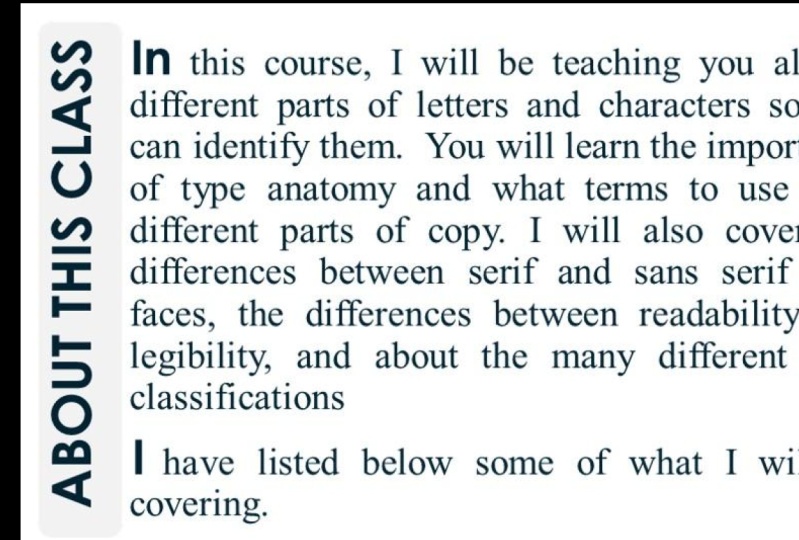
Anatomie et terminologie de la typographie
Introduction du cours
Classifications de caractères
Police de caractères, type Stlye, ou police
Anatomie des polices de caractères
Taille de caractères et mesures
Suivi de , Tracking, et direction
À propos de ce cours
Dans ce cours, je vous apprendrai toutes les différentes parties de lettres et personnages de lettres et de personnages afin que vous puissiez les identifier. Vous apprendrez l'importance de l'anatomie de caractères et les termes à utiliser avec différentes parties de copie. Je vais également aborder les différences entre les visages de caractères serif et sans seris, les différences de caractères entre la lisibilité et les nombreuses classifications de caractères différentes classifications de caractères
J'ai énuméré ci-dessous quelques-uns de ce que je vais aborder.
Terminologie
• Suivi
• Direction
• Le crénage
• Hyphenation
• Hauteur X-
• Base
• Vieux style
• Moderne
• Transition
• Stress
• Quad Em
• Grille de base
• Point vs Pica vs Inch
Anatomie
• Stem
• Bowl
• Crossbar
• Comptoir
• Ascender
• Descender
• Bras
• Oise
• Finial
• Course
• Boucle
• SERIF
• Spine
• Spur
• Caille
• Terminal
• Hauteur ascendant
• Hauteur X-
Type ouvert
• Ligature
• Alternatives contextuelles
• Ligatures de Discretionery
• Swash
• Alternatives stylistiques
• Tilter des alternatives
• Ordinals
• Fractions
1. Introduction du cours: Salut. Je m'appelle Josh Butts. Je suis graphiste et photographe. Et lorsque les aspects les plus importants de conçu pour créer une communication efficace peut être serré dans ce cours sera vous enseigner sur la typographie, anatomie et d'autres terminologie associés au type. Je vais vous apprendre comment le type est mesuré, les différentes parties des formulaires de lettres, quel suivi, laisser encourir moyens et beaucoup d'autres aspects du type de polices de caractères. Je vais également vous montrer quelques-uns de la grande ressource est que j'utilise pour trouver gratuitement des polices de haute qualité en ligne. J' espère que vous vous joindrez à moi pour apprendre tout ce que vous pouvez sur la typographie, anatomie et la terminologie. 2. Classifications de caractères: Bon, donc nous allons commencer ce cours en parlant des deux classifications les plus courantes de type, à savoir Sarah et Sansa. Et je vais le montrer plus tard pour que vous puissiez voir la différence entre ces deux classifications de type. Si vous remarquez sur les polices de caractères serif, vous verrez ces petites barbes ou serifis sur chacun des formulaires de lettre. Ces air appelé cirrus, et ils complètent habituellement les extrémités de chacune des formes de lettre. Et vous remarquerez sur San Sarah que les extrémités de chaque lettre sont simplement plates et qu'elles s' arrêtent complètement. Et l'une des façons les plus faciles de se souvenir c'est que Sands veut dire sans Sarah veut dire qu'elle a cette Sarah. Et souvent, quand vous parlez de polices de caractères San Serif, elles sont généralement appelées polices de caractères Sands. Maintenant, avec les polices de caractères serif et sans serif, il y a beaucoup d'autres classifications de types différents que nous allons examiner ici . Serif a beaucoup de styles différents en elle, et il y a, comme vous pouvez le voir ici, d' autres styles différents, et nous allons passer en revue ceux-ci un à la fois, donc vieux style est l'un des plus anciens types et vous pouvez voir qu'il est basé sur la façon dont ils construisaient le type quand ils ont commencé. Une des choses que vous remarquerez sur les polices de style ancien est la différence entre ces zones épaisses des formes de lettres et les zones les plus minces. n'y a pas beaucoup de contraste, et vous pouvez voir sur le Serifis juste ici. Ils sont assez organiques sur les formes. Juste courbe autour, et vous remarquerez également que sur certaines des formes de lettre telles que, Oh, est particulièrement, vous verrez un stress. Maintenant, nous allons parler du stress un peu plus tard dans le cours, mais comme vous pouvez le voir ici, cette ligne rouge montre le stress de ce Oh, qui fait référence à l'angle. Edwige. C' est parti. Vous pouvez voir ces zones épaisses sont sur le côté, et c'est là que les zones minces de la forme de lettre correspondent. Cela va vous dire où le stress de cette lettre forme. Maintenant. Un peu plus tard dans l'histoire, ils ont commencé à créer des visages de type transitoire et ce que vous pouvez remarquer à ce sujet est l' air de service. Beaucoup plus nette. Vous pouvez voir sur ce T leur service viennent au point direct, et il y a toutes ces lignes droites où ils courbent autour, et donc ils sont un peu plus pointus et direct sur le serifis que vous manquez aussi. Le stress sur ceux-ci est beaucoup plus vertical. En fait, c'est presque exactement droit de haut en bas, et donc vous pouvez le voir. Il devient un peu plus une police moderne avec les bords tranchants et la différence entre les zones épaisses des formes de lettres et les zones minces. Il y a beaucoup plus de contraste, et c'est donc l'une des façons de dire à quoi fait face un type de transition. Et dans ces exemples, j'ai pour l'ancien style. J' utilise l'ancien style Gowdy, et pour la police transitoire, j'utilise Baskerville. C' est une police transitoire très courante. Maintenant, nous passons ici dans les polices modernes, et vous pouvez voir qu'il devient un peu plus extrême avec le contraste et le serifis . Ces sérifis ici, comme vous pouvez le voir, sont très pointus. En fait, ils n'ont pas de transition entre le formulaire de lettre et la Sarah. Montez également ici, et vous verrez le stress sur les O est exactement droit et le contraste entre les domaines épais de la loi, réformes et les minces sont très contrastés. E. Et vous pouvez voir dans ces petites descriptions à quoi ressemble chaque classification de type et maintenant descendre ici un peu plus. Nous entrons dans les polices de caractères slab serif et vous verrez que le contraste sur les formulaires de lettre est un peu moins, mais vous en avez toujours une bonne quantité. Mais les sérifis sur ceux-ci sont très grands par rapport aux formes de lettre. Et c'est ce dont parle principalement Slab Serif, où il y a des formes géométriques épaisses, des sarah if et des lettres. Ce sont donc quelques-unes des polices de caractères serif les plus courantes que nous venons d'examiner. Maintenant, si nous venons ici, c'est une police San Serif, et celle-ci est Ariel, et c'est une police San Serif assez courante. Et ce que vous remarquerez sur les polices de caractères de San Serif, c'est généralement qu'il n'y a pas de stress pour les lettres du tout. Comme vous pouvez le voir beaucoup de ces formes de lettres, l'épaisseur est exactement la même partout, donc il n'y a pratiquement aucun contraste entre les zones épaisses et les zones d'aileron des formes Blatter . Maintenant, certaines des autres classifications différentes de type R script, et cela peut être écrit à la main ou des polices de caractères de calligraphie. Et ils peuvent avoir beaucoup de styles différents, qui reviendront un peu plus tard. Une polices de caractères décoratives. Une façon que vous pouvez dire si les polices de caractères décoratives, il aura généralement un seul style du fonds. Et donc, comme vous pouvez le voir, si je vais dans Ariel, nous irons dans les styles. Et il y a comme gras ou étroit italique mais décoratif. Si je vais dans les différents styles, il n'y a généralement qu'un seul style car ils ont été créés spécifiquement pour cela. Écoute, maintenant je reviens à la lettre noire, et c'est l'une des formes les plus anciennes de typographie, et comme vous pouvez le voir, c'est celle qui a été créée à l'origine. C' était une forme très artistique de type et nécessitait beaucoup d'habileté pour créer ça, et ça pourrait être vraiment bon pour des projets plus vintage ou quelque chose comme ça. C' était une forme très artistique de type et nécessitait beaucoup d'habileté pour créer ça, Donc Black Letter a beaucoup de courbes droites et un contraste très élevé entre certaines de ces zones épaisses et minces, et c'est un style très particulier maintenant. Le dernier type de classification de type examinera est les ornements, et cela peut généralement être construit dans deux autres polices de caractères. Par exemple, cet ensemble d'ornements est un grand ensemble dhoni d'ornements. Donc, cela vient avec que le fonds de donut, et généralement cela englobe juste un grand nombre de petits graphiques de sorte que vous pouvez utiliser avec différents types d'œuvres d'art et les résout ici. Et vous pouvez voir ces airs, les principales classifications de types que nous avons examinées. 3. Police de caractères, type Stlye, ou police: Et maintenant, nous allons regarder la différence entre une police de caractères et un plaisir. Et donc, comme vous pouvez le voir ici, sont des polices différentes que j'ai. Ainsi, une police de caractères va principalement se référer à la forme générale des formes de lettres. Donc, comme vous pouvez le voir, cette police de caractères est din et vous pouvez voir la lettre a comment elle s'étire un peu , puis se courbe autour. Alors que vous voyez Gotham, le est déjà courbé à partir de ce point, et le S a plus d'une courbe naturelle tout autour. Mais Dan a un type plus droit de courbes et de lettres droites forme des sables ouverts. Comme vous pouvez le dire, il y a cette petite coupe en haut de l'extrémité, et les esses sont un peu plus comprimées verticalement. Maintenant, on passe à cette autre police de caractères, Helvetica. Vous pouvez voir les lettres s'étirer autour de cette courbe sur le A, et il y a un peu plus de contraste entre les zones épaisses et minces de ce type. Ensuite, beaucoup de ces autres cas de type, et donc ces différentes polices de caractères ont des caractéristiques très distinctives. Maintenant, si nous allons dans certains des mêmes visages de type. Je vais conduire ça ici. Ce sont tous les mêmes visages de type, mais il y a différentes versions de celui-ci. Donc, comme vous pouvez le voir, cela a été alternatif et c'est un peu plus épais. Ce n'est pas pro, et donc ce sont tous les mêmes types de visage, mais leurs différents styles de celui-ci, et ils sont créés par des personnes différentes. Et donc, la façon dont des choses comme ça se produisent souvent est l'endroit où il y a des polices de caractères créées il y a longtemps , et les gens l'ont ramassé maintenant et en ont créé leurs propres versions. Et donc il reste toujours avec le même style où, comme vous pouvez le voir, huit s'étirent et se courbent ensuite, et c'est un dicton avec toutes ces autres versions de cette police de caractères. Mais beaucoup d'entre eux ont été créés par des personnes différentes, et il y a donc des différences subtiles, mais c'est toujours le même type de visage. Et maintenant, si nous parlons d'un fonds qui pourrait faire référence au style de type spécifique si nous parlons d'un fonds qui pourrait faire référence au style de type spécifiqueque nous utilisons sur ce sujet, donc si nous regardons ça,tout ça vient de la police centrale, que nous utilisons sur ce sujet, donc si nous regardons ça, tout ça vient de la police centrale, et chaque style fait référence à une police ou à un style de type Donc, si quelqu'un vous demande quel type de police vous utilisez sur un projet spécifique, vous pourriez dire que j'utilise central extra light métallique. Ou vous pouvez dire que vous utilisez Central Ultra. Maintenant, le groupe de tous ces styles de types dans un est appelé une police ou une famille de types, et cela fait référence à l'endroit où je suis Ah, en utilisant mon outil de type, et je crée un nouveau bloc de texte, puis je peux aller à Central. Et maintenant, j'ai tous ces styles différents dans cette famille de fonds central ou famille de type. Maintenant, une des choses que nous allons également regarder avec cela dans les styles de types est certaine. Les polices et les polices ont des styles de type différents. Et l'une des choses que vous voulez vous assurer est que vous utilisez les styles de types réels qui ont été créés avec le fonds. Et donc on va regarder ça, et c'est une police en italique, et vous pouvez voir que c'est vraiment une version, et celle-ci est fausse ou fausse. Et c'est donc ce mot photo ici est un terme commun pour le type qui se définit dans un style qui a été artificiellement créé de cette façon. Et maintenant, si on saute dans la boutique photo, c'est là que vous allez voir un peu de cette terminologie. L' utilisation est si je crée un type dans Photoshop et que je passe dans mon panneau de personnages, c'est marié. Pro et Aiken vont en italique juste ici, et ça crée son propre style de ça. Ou je peux remettre ça à la normale. Et puis je peux aller dans ce petit panneau latéral et cliquer ici faux italiques, et vous pouvez voir la différence entre ce que cela fait à ces deux polices de caractères est l' italique rial . Ses lettres ont construit une manière très spécifique. Donc ils ne sont pas étirés. Et ceci a été créé spécifiquement pour ce style. Ceci a dans la police de caractères standard a un style différent de a et il ne correspond pas aussi bien qu' en utilisant les italiques réelles pour cette police de caractères. Et si vous revenez dans Adobe Illustrator, nous avons beaucoup d'autres styles différents. Et ici, vous pouvez voir que c'est le pro adobe Gurman. Et ce qui s'est passé, c'est l'italique qui a été intégré avec le fonds, et avec cette italique, j'ai traversé et il est l'outil pur dans Adobe Illustrator et partagé cela un peu pour créer des italiques avec lui. Et il est donc toujours préférable d'aller avec l'italique qui a été intégré avec ce plaisir. Et cela va de la même façon avec les polices condensées et surtout avec quelque chose comme celui-ci, l'un des problèmes d'étirement car il peut vraiment déformer une police de caractères. Comme vous pouvez le voir, cette police de caractères que j'ai ici est Badani et est une affiche condensée. Et maintenant cette police de caractères sont ici est juste ne pas irrégulière et vous pouvez le voir avec cette police de caractères. Ces formes de lettre ont été construites spécifiquement autour de cette facilité d'air épais et mince de la police. C' est donc très proportionnel. Et avec cette version qui a été condensée ici, j'ai obtenu la police et je viens de l'insérer et elle étire la police et elle peut vraiment déformer les choses et causer des problèmes lorsque vous créez des illustrations. Et comme vous pouvez le voir, certains de ces autres problèmes que nous avons avec gras, il maintient toutes les formes de lettres cohérentes avec la police d'origine. Lorsque vous créez un fauxtexte en gras, les gens le font souvent en ajoutant un trait à ce formulaire de lettre, puis en augmentant simplement la taille de ce trait. L' un des problèmes que cela fait est qu'il commence à déformer la police en créant incohérences avec les zones épaisses et minces de plaisir. Et donc il devient presque un visage de type différent, et souvent il n'a pas l'air très bon de le faire de cette façon. Donc, surtout avec Bull, voulez-vous toujours utiliser la version originale de ce boulon ? Comme vous pouvez le voir ici, nous l'avons étendu, et c'est la même chose que je suis parti, et je suis juste allongé sur cette police, qui a étendu les tiges sur ces formes de lettre. Mais les lignes horizontales sur les formes de lettre ont été étirées encore plus minces. Maintenant, quand vous parlez de petites casquettes, comme vous pouvez le voir ici, ça devient un peu plus compliqué. Certaines polices n'ont pas de petites majuscules, et quelques fonds à faire maintenant. Cela pourrait être l'un des plus problématiques. Lorsque vous utilisez de faux ou ennemis petites capitalisations est comme vous pouvez le voir ici, cette police ici j'utilise riel petites majuscules, et les formes de lettre sont très similaires à l'épaisseur des lettres majuscules pleine taille ici dans ce faux petits casquettes composition, vous pouvez voir les petites capitalisations sont beaucoup plus petites et épaisseurs que les grandes. Et c'est parce que c'est juste le même type que les grands chats vient d'être réduit. Et cela peut créer l'amour. incohérences entre la composition et lorsque vous la lisez peuvent sembler assez mauvaises lorsque vous la comparez à la police plus grande, c' est pourquoi l'utilisation de petites majuscules riel est toujours la meilleure façon d'y parvenir. Maintenant, l' une des façons que vous pouvez dire si un plaisir a ou non de petites capsules intégrées est que vous pouvez monter à la fenêtre et vous assurer que vous avez, euh, sous le panneau de type. Vous pouvez aller à votre panneau glyphes. Et si je fais glisser ça ici, vous pouvez voir dans ce bailleur de fonds ici. Je vais cliquer dessus et je vais nous conduire un peu. Vous pouvez voir ici, nous avons ces petites majuscules juste ici dans le panneau des falaises, et cela signifie que cette police de caractères Ah , fond a riel, petites majuscules intégrées et d'autres polices comme celle-ci. Disons que j'irai à Gotham. Cela vous pouvez voir les petites majuscules ici sont beaucoup plus petites que le plafond pleine taille, et c'est parce que vous pouvez voir dans l'ensemble de paillettes il n'y a pas de petites majuscules intégrées dans le fonds, et ce qu'Adobe Illustrator fait automatiquement crée les petites majuscules. Lorsque vous êtes dans le panneau Personnages juste ici, vous définissez cela sur les petits camps. Il va automatiquement créer de petites bouchons à partir de n'importe quel plaisir que vous avez, c'est pourquoi il est important de passer à travers un panneau de verre et de vous assurer que vous savez que plaisir a vraiment de petites bouchons. Parce que si c'est le cas, Adobe Illustrator va utiliser ces vraies petites majuscules. Mais si ce n'est pas le cas, Adobe Illustrator va simplement mettre à l'échelle cette police de caractères l'une des choses les plus faciles à distinguer dans adobe dans le design. Si je vais ici, hum, je peux aller à mon panneau de préférences, et je vais aller au type avancé eso vous ouvrez vos préférences et cette section de type avancé , vous pouvez voir le petit ensemble de capuchons. J' ai mis cela à 100% et donc ce que cela signifie est quand il crée de fausses petites capitalisations, va mettre à l'échelle ces deux. Habituellement, il sera réglé à 70%. Hum, mais si je dis ça à 100% tout le temps, alors quand je clique ici et que je vais dans le panneau de mon personnage et que j'allume les petites majuscules, ça veut dire que ça va automatiquement mettre à l'échelle ces petites majuscules à ce que je mets à 100%. Et donc cette police de caractères, sbire pro il Ari a des petites majuscules intégrées, ce qui signifie qu'il va utiliser ces petites majuscules et qu'il a dit 100% de l'échelle qu'ils devraient être. Et cela signifie que ce sont des petites lettres majuscules pleine taille. Si je vais Teoh, dis Gotham, essayons juste Gotham Bold. Ces petites majuscules qu'il montre ici sont réglées à 100%, mais comme il n'a pas de petites majuscules , il est juste de mettre à l'échelle les lettres à 100%. Donc, vous n'aurez pas ce problème lorsque vous activez cette fonctionnalité. Et c'est aussi un autre moyen facile de savoir si oui ou non un correctif amusant ou de type a de petites majuscules intégrées en elle est par la mise à l'échelle de ces lettres. Et donc je vais essayer un autre. Baskerville vieux vite. Essayons juste. Je suis, oui, comme le texte Baskerville régulier. Et donc cette police de caractères n'a pas de petites majuscules intégrées. Bien, parce que ces air la pleine taille des majuscules. Et donc si je pouvais faire défiler certaines de ces différentes polices de caractères, la plupart de ces polices que je n'ai pas de petits camps par cet écran de cheveux fonder Playfair . Celui-ci le fait. Et donc ces air très légèrement plus petit que les bouchons de taille réelle. Mais vous pouvez voir que ce sont de vraies petites majuscules. Et alors revenons ici dans l'Illustrator et je vais zoomer. Je vous ai montré beaucoup de fonds différents que j'utilisais. Et maintenant je vais vous montrer quelques-uns des endroits où je trouve beaucoup de visages de très haute qualité. Souvent, on va y avoir tous ces styles. Donc, je vais aller à une nouvelle fenêtre de navigateur et l'un de mes sites préférés que je voudrais aller est polices dot google dot com. Et celui-ci a beaucoup de très bonnes polices de caractères dans beaucoup d'entre eux sont vraiment de haute qualité. Donc, dans ce site, l'un des déchets naviguer. Vous pouvez voir toutes les différentes polices ici dans l'écran principal, et vous pouvez le changer pour votre propre type. Donc exemple de texte ici et je peux appliquer cela à tous les fonds et avoir une très bonne idée de ce que je veux ressemblera à ce que je peux changer l'échelle de cela et appliquer cela à tous les fonds et voir vraiment à quoi ils vont tous ressembler. Et maintenant, si je veux filtrer ah, une certaine police de caractères que je veux. Je peux décocher ces différentes classifications de type et vraiment l'affiner. Une des choses que j'aime faire est de vérifier le nombre de styles parce que plus de styles de plaisir a, plus je vais avoir de flexibilité avec ce plaisir. Disons que je veux juste une police de caractères sands ou une police sans serif. Alors je peux vérifier ça, et je veux avoir beaucoup de styles. Et maintenant ce sont toutes de très bonnes polices de sable que je peux utiliser. J' aime son monstre dehors. Et donc si je clique dessus, ça va me montrer tous les styles qu'il a sur cette police de caractères. Et donc il en a beaucoup, en fait. Et c'est donc une ressource vraiment sympa où vous pouvez télécharger toutes ces polices gratuitement. L' une des autres ressources est que j'aime est l'écureuil amusant. Maintenant, écureuil de fonds a beaucoup de bons fonds. Beaucoup d'entre eux sont en fait des liens vers des fonds Google. Hum, et il a beaucoup d'autres très bons fonds gratuits sur Internet. Certains d'entre eux auront moins de styles, sorte que vous pouvez voir milkshake. Il s'agit d'une police décorative, et c'est une police de caractères de script parce qu'il n'y a qu'un seul style. Et donc si je clique dessus, vous pouvez avoir une idée de ce à quoi ça ressemble. Vous pouvez voir le nombre de styles et vous pouvez également filtrer les polices de caractères sur ce site Web à travers les différents styles similaires aux fonds Google. Donc, disons que je veux 12 styles ou plus et un plaisir Voici cet aileron amusant et je peux cliquer dessus et regarder quelques échantillons différents qu'il a, et je peux faire défiler vers le bas et regarder tous ces styles de type différents intégrés dans cette police famille, et ce que je peux aussi faire est de cliquer sur ce lecteur de test et d'essayer quelques-uns de mon propre exemple de texte juste là, et il va automatiquement le mettre à jour à tout ce que j'ai cet ensemble pour dire vouloir lourd et type 72 points, et cela va me donner un très bon échantillon, puis je peux télécharger le fichier de type ouvert. Et donc ce ne sont que deux vraiment bonne ressource est où vous pouvez trouver beaucoup de bons fonds de haute qualité pour vos projets. Cet air va généralement me donner beaucoup de styles et d'options différents pour travailler avec. Et si vous connaissez d'autres bons sites qui ont de bons fonds gratuits, hésitez pas à poster dans la section commentaires du cours afin que nous puissions jeter un oeil. Je vais donc revenir sur Adobe Illustrator dans la prochaine vidéo. Nous allons examiner certains des différents types de terminologie et d'anatomie des nouvelles formes de lettres 4. Anatomie des polices de caractères: Donc l'une des premières choses que nous allons regarder avec cette vidéo est comment le type est aligné. Et donc j'ai ce mot ici anatomie. Et si j'allume ces guides ici, vous pouvez voir les différents termes qu'on va passer. Hum, cette ligne de fond ici où toutes les lettres s'alignent s'appelle la ligne de base. Et je l'ai marqué juste ici. Et c'est la ligne que, comme vous pouvez le voir, la base de toutes ces lettres s'alignent jusqu'à cette ligne. Juste ici est la hauteur X, qui est l'endroit où toutes les lettres minuscules vont généralement correspondre à ou le X. C'est pourquoi on l'appelle la hauteur X. En raison de la norme X s'alignera de la ligne de base à la hauteur X. Cette zone ici est un ascender ou la hauteur du capuchon, où cette ligne sur le dessus est la hauteur officielle du capuchon. Oh, et très vite je vais te montrer un expéditeur D. Est une partie d'un formulaire de lettre qui s'étend au-dessous de la ligne de base et un US sous est une partie de ah forme de lettre minuscule qui s'étend au-dessus de la hauteur X, Cette ligne juste là. Et c'est donc ce que l'expéditeur est. Et voici les expéditeurs D. Et maintenant, nous allons revenir à notre couche d'anatomie sur cette zone où un centre comme cette lettre H que j'ajouterai juste ici. Vous pouvez voir cela correspond jusqu'à la hauteur du capuchon. Tout est sous cette véritable âme et rapide. Zoom ici et vous pouvez voir la hauteur de la cabine, la ligne de base, la hauteur X, l'Ascender ou le cap Hyatt juste ici où tout le haut correspond et la ligne de descente. Maintenant, avec des fonds différents, ils vont avoir des hauteurs X différentes et des ratios Ascender à la hauteur gardée. Donc vous pouvez voir et ces deux fonds ici, ils sont tous les deux de la même taille, les deux 87 points, hein ? Et vous pouvez regarder ça ici. Vous voyez que j'ai Baskerville et Helvetica. Et où la hauteur X correspond à Baskerville. Il est beaucoup plus bas là où la hauteur X est sur Helvetica et donc cela va faire une grande différence dans la façon dont vous allez vouloir définir votre type car le rapport de hauteur X sur Helvetica est beaucoup plus grand que sur le basket-ball. Et vous pouvez également voir que pour la même taille point Baskerville est un peu plus courte que la hauteur du bouchon sur Helvetica. Et donc ces différences aériennes, vous remarquerez dans les différentes polices de caractères. Et donc je vais les cacher et vous montrer cette prochaine série de lettres et vous montrer d'autres différences avec ces lignes. Donc ici, vous avez votre dissenteur et tous ces dissidents sur ces formulaires de lettre. Vous avez votre hauteur X sur tous ces éléments et votre hauteur de plafond, mais vous allez aussi avoir avec certaines polices et polices. Vous allez avoir différentes hauteurs de plafond et une hauteur centrale sur certains d'entre eux. Comme vous pouvez le voir ici, les majuscules sont toutes alignées sur cette ligne juste ici. C' est un combat de chat, mais vous pouvez voir ici où l'ascender il correspond pour aligner un peu plus haut que ça. Donc, si j'utilise mon outil de type et que je clique ici et un l qui va correspondre à ce même âge et vous pouvez voir comment le battage médiatique central peut souvent être la même que la hauteur du bouchon. Mais parfois, ce sera différent. Et c'est donc quelque chose que vous voudrez également surveiller lorsque vous créez un type dans vos projets. Et maintenant, nous allons y aller et regarder certains des différents termes anatomiques pour les formes de lettres minuscules. Et donc nous allons commencer ici avec le A et regarder les terminaux pour que vous puissiez voir la fin de la en fait ici, où vous pouvez voir la fin de l'E. Un terminal est la zone d'une forme de lettre où il se rétrécit et il s'arrête et va haut et montrez cette prochaine zone. C' est un taureau, et donc un taureau est en typographie, vu comme la partie incurvée de la lettre ou la partie circulaire qui englobe un compteur qui regardera dans une minute. Vous pouvez voir ici sur le P il y a un bol, et en fait, un taureau ferait également référence à cette courbe très sur le B. Vous pouvez voir sur le D. Il y a un taureau juste là et sur le remède. Il y a aussi un bol, et nous allons zoomer sur le A et haut que et vous montrer l'éperon. Ainsi, en typographie, un éperon est un petit élément de type projection qui se détache du trait principal. Et la prochaine chose que nous allons regarder, c'est la barre transversale. Maintenant à travers la barre est un trait horizontal sur une forme de lettre comme celle-ci, où il entoure une zone. Et sur cette lettre, vous voyez aussi qu'il y a cette petite zone englobée qui est appelée sur I. Maintenant, quand je parle aussi d'un compteur mais spécifique à la chaleur de la lettre, ce qui nous amène en fait à regarder un compteur. C' est ici connu comme un compteur ouvert, et ainsi de suite. compteur ouvert comme celui-ci est l'espace partiellement ouvert qui est à l'intérieur d'un personnage. Mais c'est ouvert à un bout, et nous allons regarder ça juste ici. Vous pouvez voir que cette zone qui est ouverte est appelée l'ouverture, et l'Apatow fait référence à l'écart qui crée un compteur ouvert. Maintenant, nous allons les cacher et vous montrer. La prochaine chose avec les compteurs est les compteurs fermés maintenant. La plupart de ces formulaires ont des comptoirs fermés. Vous pouvez voir dans le O et le G, Aussi dans le p Q B amedy ces air tous les compteurs proches, qui est une zone qui est juste complètement enfermé par un personnage. Je viendrai au F comme on l'a dit tout à l'heure. Ceci est connu sous le nom de Sarah et sur le F. Il y a aussi un trait transversal, euh, maintenant à travers le trait est une ligne horizontale dans une forme de lettre similaire à la barre transversale, mais il n'est pas inclus dans la forme de lettre. Donc, comme vous pouvez le voir dans la lettre T, il y a aussi à travers le trait juste là maintenant, aussi particulier à la lettre F. Vous verrez que cette partie supérieure est connue sous le nom de fenouil. Fenouil est la partie supérieure de la courbe de assez qui arrive à une fin et passant à la lettre G. Il y a quelques parties différentes de la lettre G que vous verrez sur le dessus est le taureau, mais sur le fond est appelé une boucle, et maintenant boucle est un particulier à un G minuscule dans la plupart des polices de caractères, où il y a ce qu'on appelle une forme de lettre à deux étages. Maintenant, la forme de lettre de deux histoires est là où il a deux de ces parties. Comme vous pouvez le voir dans cette lettre ? R. C'est ce qu'on appelle deux histoires A Non. Si j'ajoute un autre type de dans un, euh, je vais le conduire ici, et je vais l'agrandir et ensuite je pars. Teoh, utilisez un Berlin Sands. Maintenant, c'est ce que vous appelleriez juste une seule histoire où c'est seulement dans la partie inférieure de la forme de lettre, où c'est une histoire de deux. Ça reviendra ici à la prison où c'est une lettre de deux histoires. G sur la boucle sur un G est la zone complètement fermée qui est généralement inférieure à la ligne de base, ce qui serait là où le bas de ces lettres se réunit. Et maintenant sur une double histoire G, où cela se connecte ici, la boucle et le taureau est appelé un lien et voir l'énergie concessionnelle. Il y a en fait beaucoup de termes différents quand on fait référence aux différentes parties de celui-ci , surtout cette petite zone juste ici en haut du G est connue sous le nom d'oreille. Maintenant, les années que l'on trouve habituellement sur la lettre J, et c'est un peu décoratif sur le dessus du bateau, donc je vais les cacher maintenant et nous allons passer à la lettre G. Et vous pouvez voir que c'est similaire dans certaines de ces autres lettres s'appellent L'Épaule. Maintenant, l'épaule est un coup de courbe qui commence à la jambe d'un personnage comme lettre N ou H, et même dans la lettre M et un coup de foot qui vise vers le bas sur ces lettres et je vais zoomer sur la lettre I et toi peut voir cela le petit point sur le haut de la minuscule Ira J, est appelé un point ou un tittle, et c'est donc assez explicatif. Maintenant, dans cette lettre suivante, voici Ah, lettre J minuscule La petite extrémité effilée d'une forme de lettre s'appelle la queue Vous pouvez voir sur la lettre minuscule T . Il y a aussi une queue. Et si vous descendez à la lettre, pourquoi vous pouvez voir un conte qui descend en dessous de la ligne de base  ? Cela reviendra ici et ira à la lettre suivante sur une lettre K. Vous pouvez voir une tige est une barre verticale primaire sur une forme de lettre. Donc, comme vous pouvez voir la tige de la lettre, je suis juste ici. Et beaucoup de ces autres formes de lettre ont une tige. Aussi, vous pouvez voir ici sur la lettre f sur l'être ces air toutes les tiges primaires de ces lettres. Si vous revenez, nous allons voir maintenant la jambe est la partie en pente vers le bas de forme de lettre ah, généralement sur Ah que ou les majuscules sont qui ralentit de la lettre. On va passer à la course. Maintenant. Le trait est sous toutes les formes de lettre. Généralement, un trait est une partie principale du formulaire de lettre qui crée la lettre dit que vous pouvez voir dans le P. Le trait est ce qui constitue cette lettre. Et dans le O maintenant, pendant que nous regardons le oh, nous allons regarder le stress comme nous avons parlé plus tôt. La contrainte est une diagonale, une inclinaison de n'importe quelle forme de lettre. Donc, si vous y pensez, j'ai téléphoné. Il aurait beaucoup plus de stress que ces formes de lettre maintenant pour venir ici à la s. Ce trait ici est le trait principal de la courbe de la minuscule, ou lettre majuscule s qui est connu comme la colonne vertébrale et vous verrez. Aussi dans la lettre s est un bec. Maintenant, le gros est l'éperon pointu qui se trouve habituellement en haut des lettres dans ces formes de lettres romaines . Maintenant, nous allons venir ici aux dernières lettres de l'alphabet où nous allons voir sur le V et le W aura. Vertex est le Vertex est généralement juste le point extérieur au bas d'un personnage où deux de ces traits se rencontrent. Et de l'autre côté, vous verrez l'entrejambe juste ici, aux Émirats arabes unis. L' entrejambe est cette zone de la forme de lettre sur le dessus de l'endroit où deux de ces coups de viande et créer cette partie du comptoir. Et la dernière chose L. C dans ces lettres est le trait diagonale. Et c'est la même chose que vous verrez dans ces autres coups juste ici. Le trait diagonale est sur ces lettres en bas, où le trait primaire principal est en diagonale. Et donc, zoomez sur toutes ces formes de lettre et nous les cacherons. Et maintenant, regardez les formes de lettres majuscules. Et donc nous allons recommencer avec un vous remarquerez avec une majuscule. R. C'est comme un V à l'envers où ? En bas de la vue. Tu te souviens qu'on avait eu le Vertex juste ici ? Eh bien, avec un A, le sommet de ça va être appelé les animaux de compagnie A. Et c'est ce que vous appelez la zone du sommet. Où diagnostiquer les coups d'une lettre pour la viande. Et encore une fois, comme nous l'avons vu, nous avons la barre transversale sur un qui est le trait horizontal qui traverse une forme de lettre. Et on va bonjour, Viz puis on a la lettre C. On a notre comptoir ouvert et la zone où il ne se connecte pas s'appelle l'Apertura. Et vous avez nos comptoirs de vêtements, euh, dans la lettre o et dans la lettre Q, où l'intérieur de la forme inférieure est complètement fermé. On va les prendre maintenant et regarder le bol. Donc, beaucoup de ces termes que vous pouvez voir sont assez similaires à partir des lettres minuscules. C' est sur la minuscule A. Il y a un éperon et vous pouvez voir dans un certain nombre de cas Gee, il a aussi un éperon qui s'étend à partir de cette forme de lettre. Il y a des queues sur la lettre J et la lettre Q comme une queue très particulière dessus, qui est assez perceptible. Et sur la lettre K, comme nous avons parlé il ya ah, jambe, jambe, et en majuscules, les lettres sont vous pouvez aussi voir que la jambe maintenant les tiges sont les mêmes barres verticales droites sur les formes de lettre Comme vous pouvez le voir ici dans la lettre T et dans la lettre l un des différents termes que nous allons regarder ici, cependant, sur la lettre l est cette zone juste ici qui s'appelle le bec. Et comme il a vu que sur la lettre s dans l'ensemble précédent de lettres minuscules juste ici à la fin de ce s est un bec. Eh bien, une lettre majuscule. J' ai aussi ce gros maintenant. Eh bien, nous sommes de retour ici en regardant Serifis. Je vais vous montrer ces zones sont appelées parenthèses et c'est une distinction d'un serif où un surf pourrait être exactement droit ou les crochets pourraient être inclinés un peu plus dans la lettre o, nous avons du stress, qui est l'angle de celui-ci et qui passe à la lettre s. Il y a la même colonne vertébrale, qui est ce trait incurvé primaire qui compose la lettre dans la lettre T. Nous avons un bras maintenant le bras est vers le haut. Course inclinée ou juste droite vers le haut qui ne se connecte à aucun autre trait de part et autre. Donc, sur cette lettre, vous pouvez voir qu'il a un bras ici, et de l'autre côté de ce serait un autre bras les connaît. Et nous avons regardé cela avant le sommet sur le V et sur le bas de la W. Il y a aussi ces deux Vertex est, Et sur la lettre Z, nous avons la même diagonale frappé que nous avons vu dans la forme de lettre minuscule. On va cacher ça. Et maintenant, regardez ces deux types quelque peu uniques de ces formulaires de lettres avec nous. voyez, vous pouvez voir cette zone qui s'appelle la barbe qui est un serif qui vient autour et qui pointe vers le haut sur la lettre C et vous pouvez voir à quoi ça ressemble. Un peu comme une barbe. Et pour certaines lettres ou fonso, vous aurez la zone Vissel qui s'étend de différentes formes de lettres qu'on appelle un swash, et il se trouve généralement dans des visages plus décoratifs. Ou parfois il y aura différentes options pour certaines polices de caractères que vous pouvez y ajouter une neige fondante . C' est également le plus courant dans les polices de caractères de script qui vont avoir ces lavages de différence. Donc, je vais faire un zoom arrière, et maintenant nous allons regarder quelques différentes fonctionnalités de type ouvert. Ainsi, lorsque vous installez un fonds, la plupart des polices seront soit de type vrai, soit de type ouvert. Si vous avez un front de type ouvert, vous pouvez aller sous la fenêtre et aller à votre panneau de type ouvert, eso, qui tout tirant juste ici. Et je vais vous montrer comment utiliser quelques-unes de ces différentes fonctionnalités avec vos polices de caractères . Donc la première chose que nous allons regarder, c'est ici, et ce sont des ligatures. Ainsi, les ligatures ont été créées par des concepteurs de type lorsque deux lettres qui étaient à côté de l'autre causent des problèmes quand elles se rapprochaient vraiment. Vous pouvez voir ce que j'ai sans effort ici quand ils sont à côté de l'autre qui est si proche qu'il crée cet espace inconfortable. Et donc ce que les concepteurs de type ont fait est créé dans beaucoup de fonds différents. Ces ligatures, qui sont des connexions entre les lettres qui peuvent causer des problèmes quand elles sont trop proches les unes des autres. plus souvent ces lettres R fl si j'impliquais habituellement la lettre f et L, et quand vous tapez où vous pouvez faire est, ah, je vais aller à mon outil de type, Et je vais juste commencer avec beaucoup dans pro parce que c'est une très bonne police pour montrer cet exemple avec, et puis je vais juste cliquer ici et taper F f l. Et vous pouvez voir ici. Il n'utilise pas les ligatures parce que j'ai dans mon panneau de type ouvert, les ligatures juste ici, liqueurs standard sont désactivées, et de cette façon ces lettres ne font que taper les lettres standard de la police. Donc Aiken Dio est supprimer ceux et allumer les ligatures. Et puis quand je tape appel comme ça, ça va automatiquement les connecter quand je n'ai qu'une seule lettre. Il tape simplement la lettre standard, mais il peut automatiquement reconnaître quand une ligature est nécessaire, en fonction des lettres qui sont à côté de l'autre. Donc si j'avais un L ça va automatiquement connecter ça ou un F et un oeil. Il relie automatiquement ces lettres. Donc je vais juste dilater ça et revenir. Et donc ce sont des ligatures. La prochaine chose que vous pouvez regarder est juste ici est des alternatives contextuelles. Et je vais te montrer dans ce fonds juste ici. C' est Aphrodite E. Et si je les supprime et que je tape simplement un s standard, c'est juste un s standard de la police. Mais si je tourne sur des alternatives contextuelles, alors va ajouter une des formes de s alternatives pour ce visage de type. Et si vous allez dans votre panneau glyphes sur votre type de fenêtre et vos falaises, alors je peux le faire glisser. Vous pouvez voir ici pour que si je sélectionne cela, vous pouvez voir qu'il est juste ici dans la police de caractères. Et si je vais sous ce petit panneau juste ici où il dit montrer et ce menu déroulant, je peux trouver toutes ces alternatives goto alternatives, ou je vais en fait aller alternatives pour la sélection actuelle. Et je vais zoomer un peu et vous pouvez voir Ce sont quelques-unes des différentes alternatives que vous pouvez utiliser. Et si vous utilisez la dernière version d'Adobe Illustrator simplement en sélectionnant une lettre, vous pouvez consulter automatiquement certaines de ces différentes alternatives ici. Et c'est la bonne chose à propos du panneau de type ouvert est Vous pouvez vérifier cela sur. Donc, par défaut, va utiliser les alternatives intégrées pour cela, et vous pouvez passer par et je change manuellement celles que vous voulez. Et donc toutes les polices ne vont pas avoir toutes ces options différentes. Vous pouvez voir que j'utilise le lierre d'effort, et il n'a pas le Zordon ALS ou les fractions. Et donc, selon le type de visage que vous avez, cela déterminera quel type d'alternatives vous avez pour cela. Donc, je vais déplacer cela ici, et c'est un similaire avec une alternative stylistique utilise à ST Method cette police de caractères adobe un pro du gouvernement. Et donc si je l'aime juste là et éteins les alternatives stylistiques, alors ça va juste taper un e régulier. Mais si je l'allume, alors va ajouter une petite alternative vous à cette forme de lettre. Ou je pourrais ajouter un R ou l'activer et à un autre type de dans notre et ainsi avec une alternative contextuelle et stylistique, comme vous pouvez voir que vous pouvez facilement accéder à quelques options différentes pour certains fonds assez facilement juste en vérifiant ceux sur assez. Et ce sera la même chose avec ces autres types de lettres utilisant ligatures discrétionnaires. Ceci est similaire à la F et je est ensemble avec la mer et ce thé. Si j'ai vérifié ça ici, ligatures discrétionnaires et je m'en fais sans, alors ça va relier ces lettres ensemble. Vendu. Supprimez-les ici. Maintenant, plus tôt, nous avons parlé de swash is et des formes de lettre, et c'est de retour avec la police Aphrodite E à nouveau, et c'est juste une forme de lettre régulière. Mais si je vérifie le swash est des alternatives juste ici. Swash. Ensuite, quand je tape une journée, cela va ajouter une croix différente sur ce formulaire de lettre, et cela peut vraiment vous donner beaucoup de flexibilité lors de la création de certains paramètres de type pour créer un type amusant et artistique. Maintenant, on va aller voir les fractions et les polices de caractères Gordon ALS auront deux types de lettres et une barre oblique entre elles. C' est fait spécifiquement pour les fractions. Donc beaucoup de gens vont parfois taper une fraction, et ils vont simplement aller ici et taper, vous savez, cinq barre oblique huit. Et ce n'est pas la bonne façon de faire une fraction, parce que ces caractères standard de l'air et ils ne seront pas une fraction complète de la façon dont il devrait être tapé. Et ce n'est pas la bonne façon de créer des fractions. Une des façons de le faire de la bonne façon est d'entrer dans une police de caractères. On va cliquer ici, et tu trouveras le poste. Et il y a toujours un numérateur et un dénominateur lors de la création de fractions. Donc, si je vérifie le numérateur et que les nombres que je tape seront dans la position de numérateur d'une fraction. Et donc je suis et laisser ces et de créer le SLASH. Si vous ne voulez pas aller dans le panneau des falaises et essayer de trouver ces différents personnages, Aiken sur un Mac et un PC, je peux juste appuyer sur option ou arrêter et déplacer et un et cela va créer la barre oblique juste ici, qui est une barre oblique qui ira entre une fraction. Et je Si je vérifie ma position sur le panneau de type ouvert et avait dénominateur et je tape un autre nombre, il va être dans la fraction exacte Foreman et la façon dont vous pouvez vérifier que ces fractions ont été créées juste est que vous pouvez aller dans le panneau glyphes et tous zoomer un peu et aller à l'endroit où se trouvent certaines des fractions pré-construites. Et je vais juste taper trois forces et vous pouvez voir qu'ils sont sur les mêmes niveaux. Ce trois correspond à ça pour et que quatre correspond à cinq et les barres obliques air de la même façon. Vous pouvez voir si j'utilise des barres obliques standard ici. Ceux-ci sont beaucoup plus grands, et ceux-ci ne fonctionneront pas pour les fractions. Et donc c'est, ah, une façon vraiment simple de créer des fractions précises. Maintenant, une chose juste de savoir ces air seulement avec des fonds spécifiques, certains fonds n'auront pas de caractères ou de formulaires de lettre. Ils ont été créés spécifiquement pour les fractions, et donc gardez cela à l'esprit et une autre façon vous pouvez facilement les créer. L' utilisation du panneau de type ouvert est littéralement ce type. En utilisant la vente aux enchères de fraction, je peux automatiquement taper des fractions en utilisant la barre oblique, et je n'ai pas besoin d'utiliser aucun de ces raccourcis. Mais avec certaines polices de caractères, cela peut ne pas toujours fonctionner, et donc gardez cela à l'esprit. Et maintenant, l'une des autres choses allait être celle d'Ordell. Et donc quels tsar orginal sont des lettres en exposant ou des chiffres qui viennent directement après le premier personnage ? Ceci est généralement vu dans les nombres où vous dites troisième, quatrième ou deuxième, et donc une façon facile de le faire est d'utiliser cette ordonnance. Cochez Mark, et il va essentiellement créer des lettres en exposant comme ceci après le premier caractère . Donc j'ai un quatre et n'importe quoi après ça avant qu'un espace soit en exposant. Mais alors si je frappe un espace et que je tape un autre caractère, alors cela va être un caractère pleine taille et les lettres après cela vont toujours être en exposant, et ce sera le cas avec les mots à la première lettre du mot sera toujours dans un caractère pleine taille et le reste de ce mot avant l'espace après qu'il sera dans l'exposant. Et donc après son nom ici, vous pouvez voir tout ce que nous avons regardé dans cette vidéo impliquent la terminologie générale et un ennemi des formes de lettres. 5. Taille de caractères et mesures: maintenant, dans cette vidéo, nous allons voir comment ce type n'est pas mesuré. Et donc j'ai un genre ici. Et si vous cliquez dessus, cela est défini en 72 point. Maintenant, quand je dis 72 points, ça ne fait pas référence à cette distance du W au bas du pourquoi. En fait, ça fait référence à ça ici. Um, quand le type a été créé à l'origine, il a été créé en blocs, et ces blocs avaient une lettre sur chacun. La façon dont il est mesuré est du bas de ce bloc vers le haut, qui s'appelle un M. Et donc le type de mesure est du bas de la lettre la plus basse au haut de la lettre la plus haute. Et puis il donne un peu de rembourrage supplémentaire en plus de ça. Et donc vous pouvez voir que c'est 72 points dans cette ligne juste ici montre la distance d'un bloc de 72 points, et de sorte que, comme vous pouvez le voir, c'est un M, et souvent, ils utiliseraient l'espacement et si utilise ces lorsqu'ils créent des espaces sur des lettres. Et ces blocs étaient à la même distance horizontalement que verticalement, et cela est appelé sur em quad ou un carré M parce que c'est un M horizontalement et un m verticalement. Par conséquent, si vous avez déjà eu de l'expérience dans le codage ou le développement, vous avez peut-être entendu parler d'EMS avant d'encoder habituellement sa référence à un pourcentage de la caractères parent. Et c'est ce qu'il vient est basé sur un Taipei de 72 points. Et maintenant, si vous vous demandez quel 72 point fait référence à Teoh, je vais monter ici et la façon dont le type a été mesuré est en points pikers ou pouces. Et donc il y a 72 points dans un pouce, et donc cela signifie de cela juste ici d'une traînée ces un peu vers le bas. Ensuite, vous pouvez voir que ce serait un pouce de haut du haut de cette ligne au bas d' ici pour le type. Et il y en a aussi six. Pike est dans une niche, et donc un six pica est une image serait également égale à Si je le mets ici 12 points dans un pica, et cela vous donnera une bonne référence pour la façon dont le type est dimensionné lorsque vous créez le type . Il vous donnera un bon point de référence, et vous pouvez comprendre comment le type a été créé à l'origine 6. Suivi de , Tracking, et direction: Bon, donc la dernière leçon me manque. Nous allons examiner quelques méthodes différentes de réglage du type à partir du panneau de caractères. Donc, je vais glisser dans le panneau de caractères juste ici. Et l'une des premières choses à parler est le suivi, et donc le suivi que vous pouvez voir est juste ici. Et c'est la distance entre tous les caractères et l'un des raccourcis faciles que vous pouvez utiliser un illustrateur adobe. Lorsque vous sélectionnez tout votre type est à l'aide de ce panneau, vous pouvez cliquer vers le haut ou vers le bas sur qui va uniquement suivre dans ces formulaires de lettre. Maintenant, si je maintiens, le décalage va changer cela de 10 points à la fois. , Ce que je préfère faire,c'est utiliser le raccourci clavier, qui, qui, comme vente aux enchères ou Ault et touche flèche gauche ou flèche droite, qui va automatiquement suivre ces lettres plus rapprochées ou plus éloignées. Maintenant, tourner est un peu similaire au suivi sauf Kern. ING fait référence à la distance entre Onley deux lettres, et donc le suivi est la distance entre toutes les lettres et Kern ing est quand vous avez deux lettres qui sont trop proches les unes des autres. Par exemple, vous voyez ce E dans ce sont là trop proches ensemble et donc je peux faire est de cliquer juste entre ces lettres et de passer ici, qui est le Kern ing, et je peux changer ce décalage en maintenant augmenter que Kerney et ce que je peux aussi faire est similaire au même clavier. Raccourci est juste en cliquant droit entre deux lettres et en maintenant l'option ou tout. Et juste de tourner ces lettres et ce que je veux faire d'habitude, c'est trouver une référence pour ces lettres. âme est généralement comme la distance entre deux lignes droites et essayer de faire cette distance égale entre toutes ces formes de lettre elle-même juste ici entre notre dans em, Je pense que cela semble assez bon. Et puis je vais diminuer cette distance ici. Et maintenant, si vous regardez cela, cela semble beaucoup mieux que quand il l'a fait avant que l'un des termes, ils peuvent trouver que certaines personnes se référant à gagner du porc est Keming, qui est une sorte de jeu sur le fait que lorsque le sont et le M est trop proche ensemble, cela ressemble à venir, et donc venir est juste le résultat de Kerney mal fait. Et donc l'un des endroits où vous pouvez aller est ce site ici, tapez méthode point a c et je vais l'ouvrir dans un navigateur ici. Et voici ah, site Web d' entonnoir qui vous aidera à pratiquer Kerney. Eh bien, ce que vous pouvez faire pour commencer, c'est que vous déplacez juste une de ces lettres et ensuite cela vous fait commencer sur ces différentes pratiques, les polices de caractères et la façon dont vous le faites, c'est que vous pouvez cliquer sur les différentes lettres, et ensuite, vous les déplacez exactement là où vous pensez qu'ils devraient aller. Et je pense que c'est assez proche. Et puis tu as frappé. Comparer. Il va vous montrer une comparaison de l'endroit où se trouve le Kern ing en réalité. Et puis vous pouvez regarder la solution pour voir ce qu'elle devrait vraiment être. Regardez ce que vous avez fait et vous pouvez voir le boulon de comparaison. Et donc si vous en faites quelques-unes, alors je vous donnerai une bonne pratique sur votre tournage comme ça. Je peux déplacer ce p sur un peu, puis appuyer sur Comparer et c'était en fait assez proche. Et donc si vous allez simplement taper la méthode point a c, alors cela va vous donner ce site Web qui vous aidera à pratiquer certains de vos différents tournages. Revenons donc à Adobe Illustrator et il y a d'autres choses que je vais vous montrer dans le design. Et donc beaucoup de raccourcis, ils vont être similaires entre Photoshopped et ce sera illustrateur et dans le design. Si je crée est mon outil de type et de créer une boîte et je vais faire un clic droit et remplir cela avec du texte d'espace réservé et je peux sélectionner tout mon type. Et avec cela, je vais augmenter l'espacement entre ces lignes et cela s'appelle laisser, et vous pouvez le voir dans le panneau de caractères juste ici. C' est un leader, et donc si je le suis, augmentez cela, alors l'espacement entre ces lignes va augmenter. L' une des choses que cela va aider avec le plus est la lisibilité, et maintenant, ces air à virages qui sont en fait assez importants dans la typographie est comprendre la différence entre lisibilité et lisibilité. Maintenant, je vais déplacer ce type juste ici, et je vais le copier, option enfoncée et en faisant glisser ça là-bas, et je vais faire le contraire. Évitée avant. Et vous pouvez voir si vous deviez regarder ces deux paragraphes séparément lorsque vous lisez quelque chose. Lequel serait, selon vous, plus facile à lire ? Je dirais que la plupart des gens pensent que ce paragraphe sera plus facile à lire parce que les lignes s'espacent beaucoup plus confortablement, et je ne me sens pas très maladroit de lire cela. Où est ça ? Je regarde ces lignes qui sont vraiment proches les unes des autres, et vous pouvez voir certains des expéditeurs D commencent à heurter les expéditeurs sur cette autre ligne. Et donc ce n'est pas vraiment bon. Lorsque vous définissez le type, ce dont je parlais juste là concerne la lisibilité de ces paragraphes, parce que maintenant, si vous entendez le terme capacité de rebord qui fait référence à la capacité de distinguer certains formes de lettre en dehors des autres formulaires de lettre, et vous pouvez donc voir ce type ici. Je place la capacité de rebord n'est pas aussi bonne parce que ces formulaires de lettre sont tous mélangés, et ils ne sont pas écrits très proprement. Et maintenant, cela peut être quelque chose que vous voulez pour un style particulier pour un projet. Mais en général, vous voulez que la capacité de rebord, en particulier pour les grands paragraphes, soit très lisible. Et un autre mot pour ces paragraphes serait café. Maintenant, vous avez peut-être entendu parler de copie avant, mais si vous n'avez pas de copie est juste un autre mot pour le type ou le texte sur une page. Alors maintenant, je vais les supprimer. Et si nous revenons à comprendre la lecture de ces paragraphes, l' une des meilleures règles est que j'aime suivre est que plus la hauteur X d'une certaine police de caractères est élevée , plus vous voudrez généralement avoir la tête. Et donc je vais le faire. Ce paragraphe ici et copiez cela. Et je vais utiliser une police de caractères. Helvetica, parce que je sais que cette police a une hauteur de X beaucoup plus grande que Baskerville, que j'ai ici. Donc ce paragraphe pourrait avoir un peu trop de début et le raccourci que vous pouvez utiliser pour augmenter ou diminuer la vie est similaire à celui d'un illustrateur que j'utilisais Option et de droite et gauche Eric E. Mais au lieu de cela, cette fois, j'utilise la touche fléchée vers le haut pour diminuer laisser sur un bas pour l'augmenter. Et donc, si ça, je veux qu'on les laisse juste un peu plus comme ça. Et maintenant, cela se lit beaucoup plus bien. Et avec ce paragraphe Helvetica juste ici, je pourrais garder que laisser assez cohérent où il est, parce que puisque la hauteur X est un peu plus grande, vous voulez plus d'espace entre ces lignes de texte où vous voyez ce visuel vide Et donc j'espère que vous apprécierez ce cours. Et si vous ne l'avez pas s'il vous plaît donner un avis pour que d'autres personnes puissent profiter aussi.